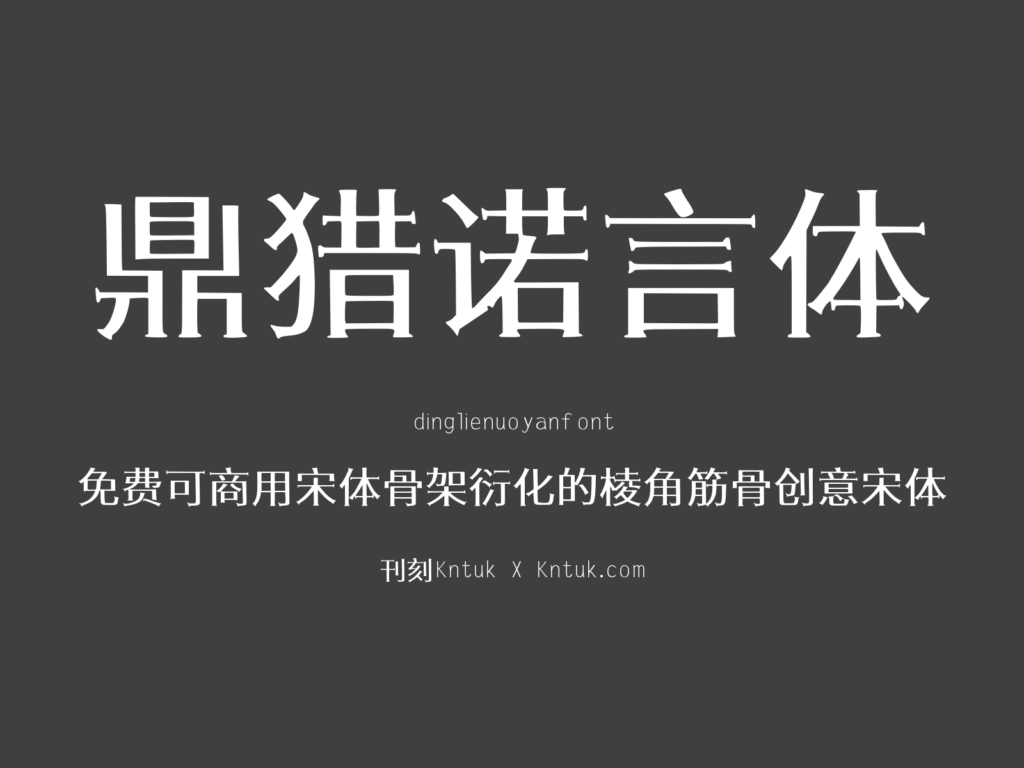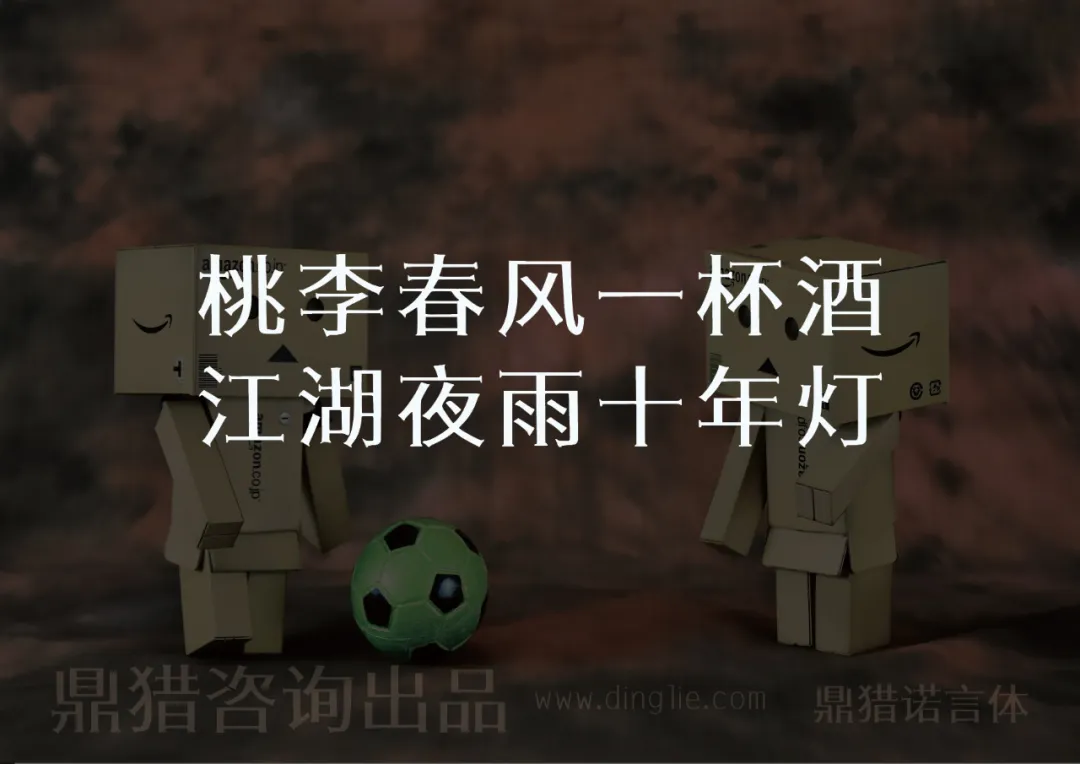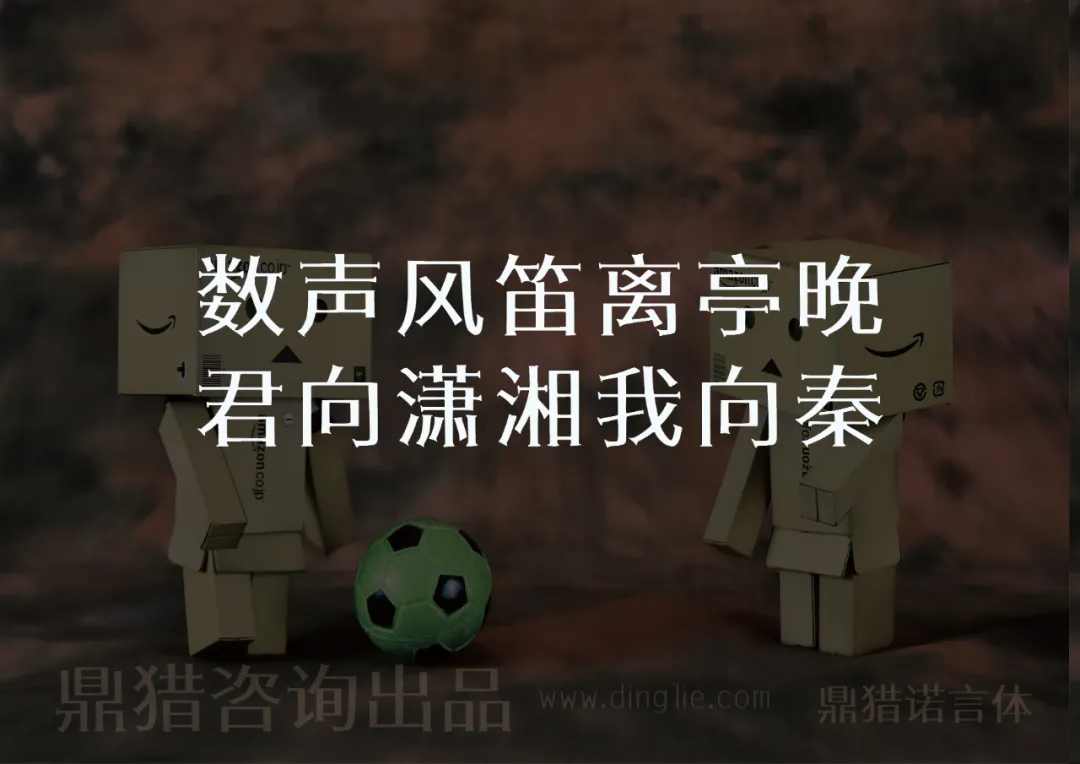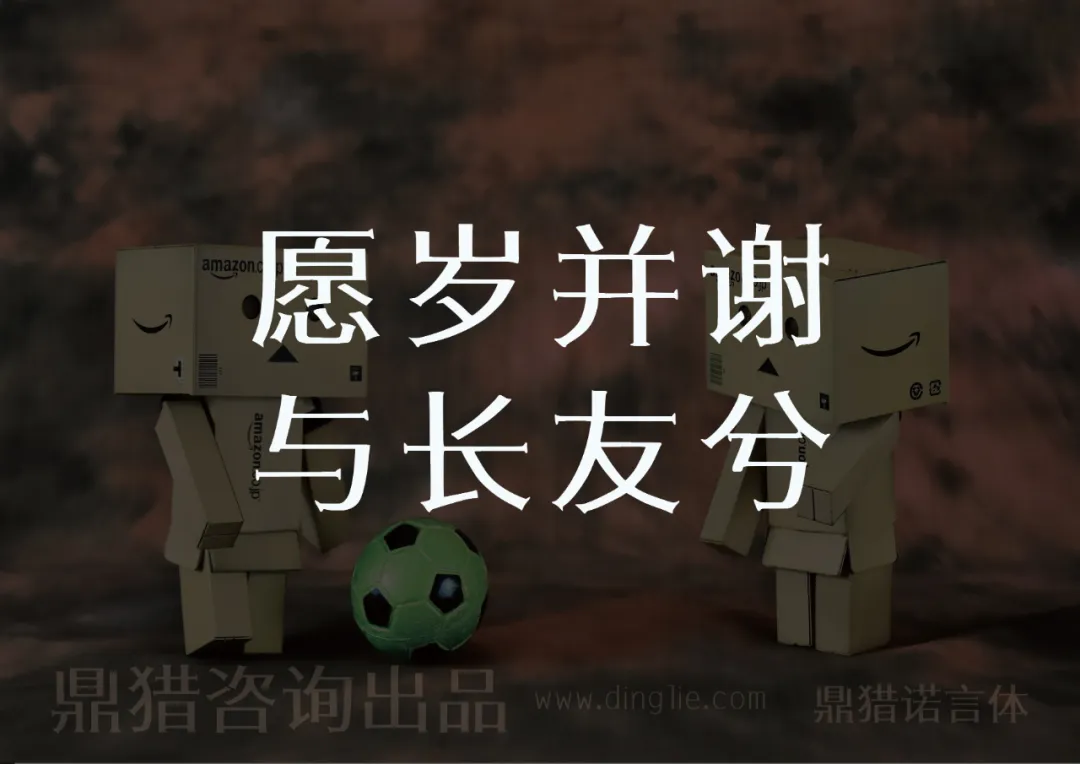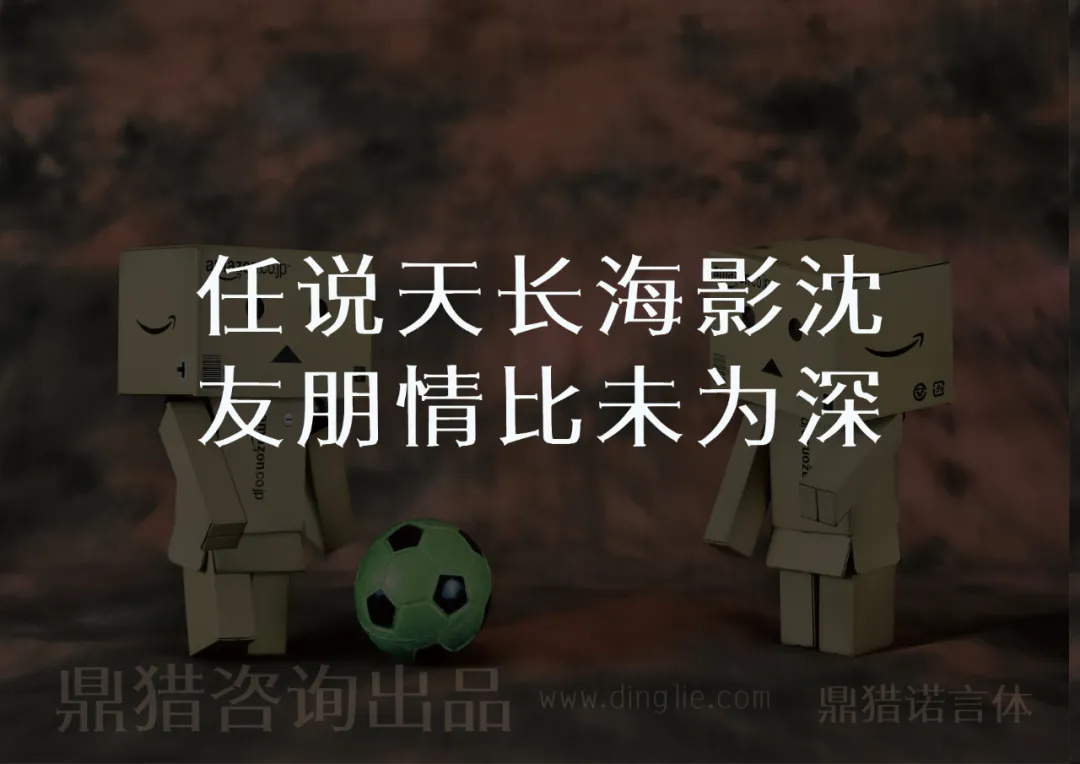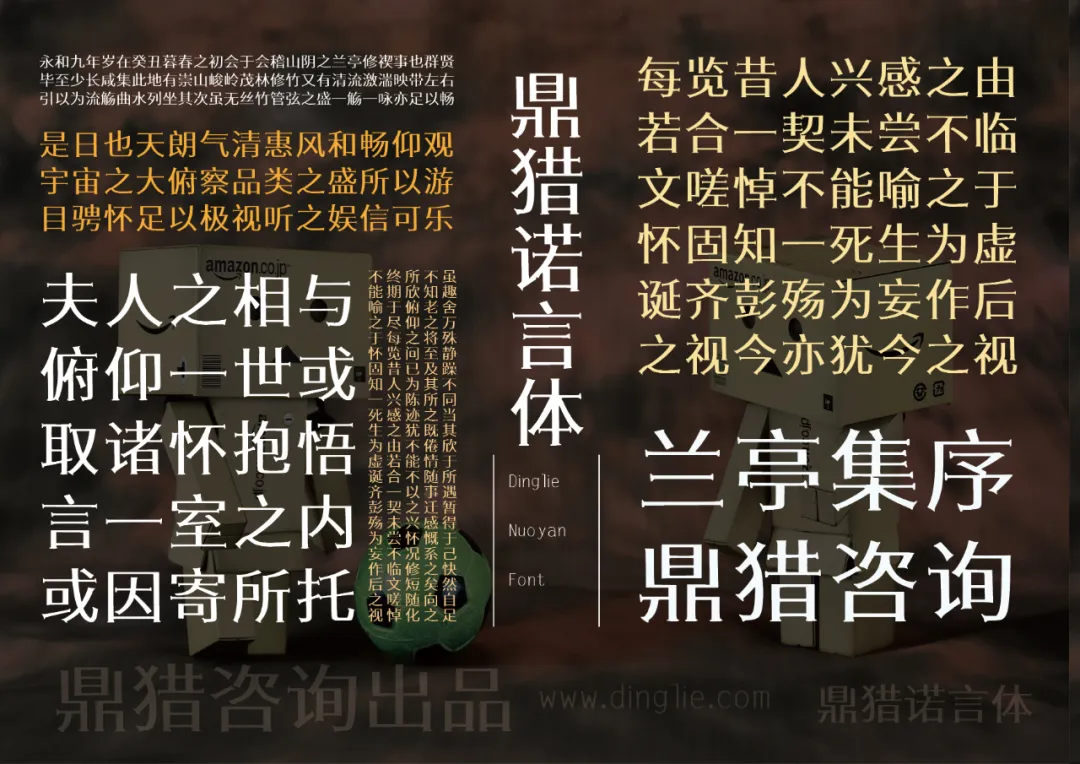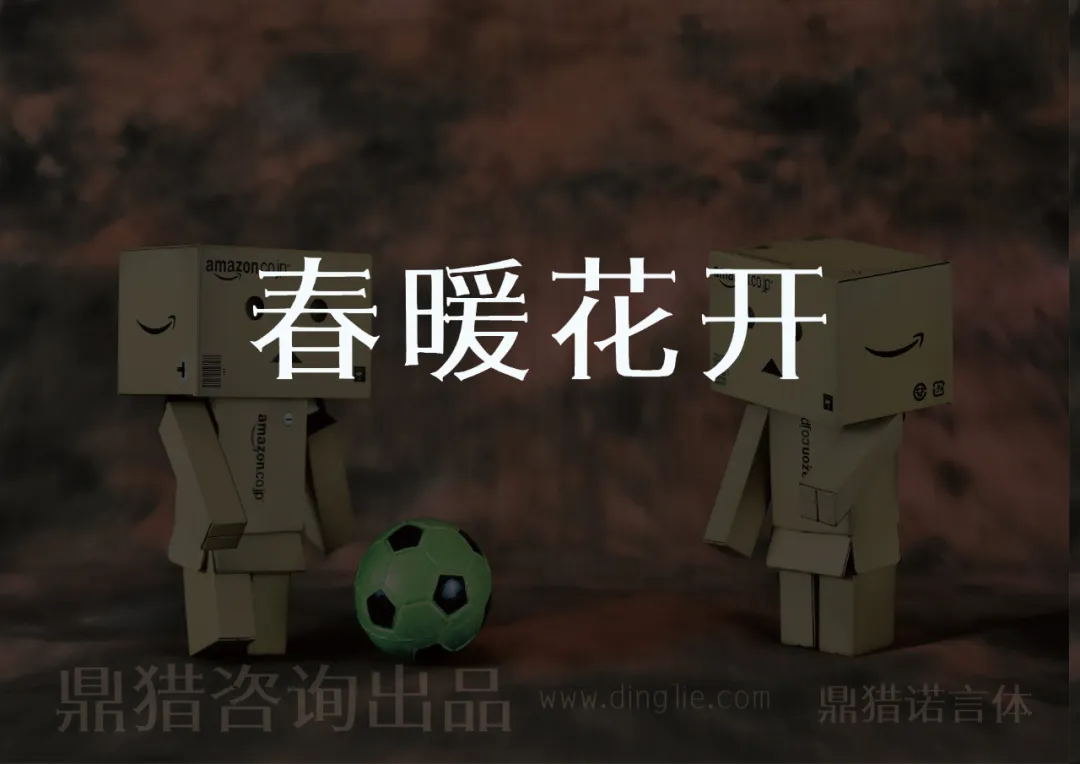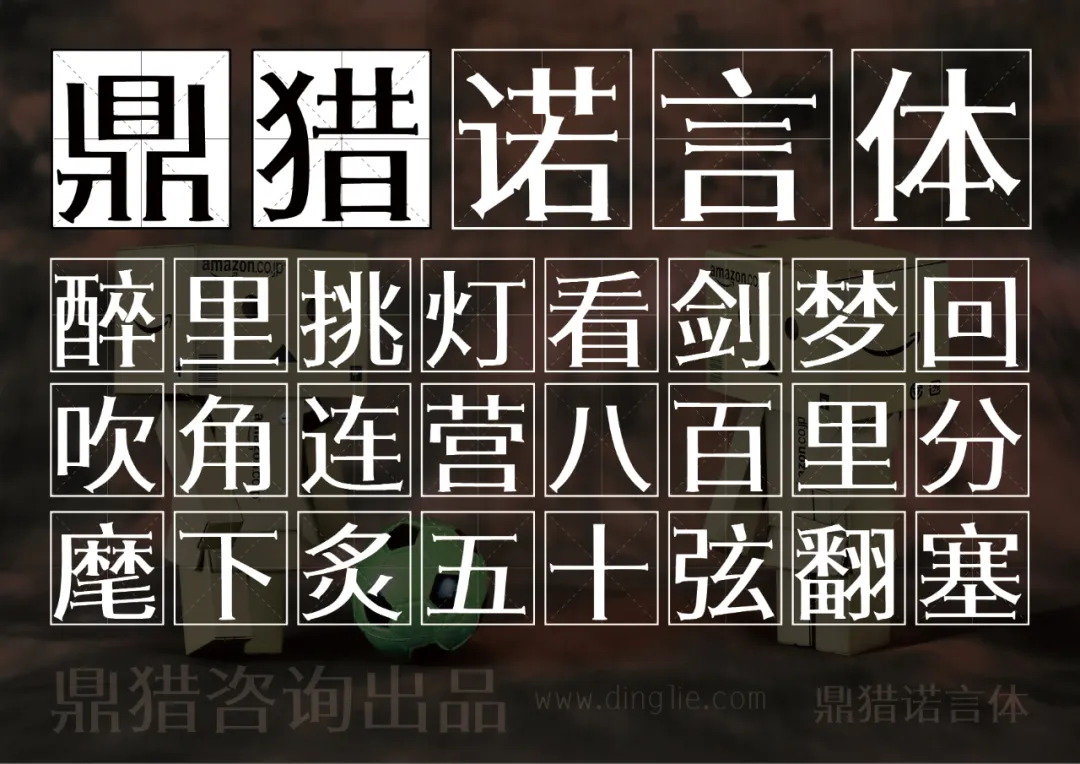
鼎猎诺言体,是一款以宋体为蓝本衍化的创意字体,整体有棱角但内里有筋骨,有着一诺千金和一言九鼎的稳健,也有自主自立的棱角。鼎猎诺言体适合美食餐饮、文化艺术展览、企业文化,以及封面杂志海报、餐饮茶饮、美妆护肤等各个行业。
鼎猎诺言体字体样张,展示“醉里挑灯看剑梦回,吹角连营八百里分,麾下炙五十弦翻塞”,底部标注鼎猎咨询出品及网址www.dinglie.com-刊刻Kntuk
鼎猎诺言体以简体中文汉字编码国家标准(GB2312编码)为标准,
共计设计了多达7415个字符,其中汉字6769个。
可以满足绝大部分印刷设计等要求。
鼎猎诺言体字体展示,以《兰亭集序》文本为例,鼎猎咨询出品,网址www.dinglie.com。-刊刻Kntuk
愿岁并谢与长友兮,两个亚马逊纸箱人中间有一个足球,鼎猎咨询出品鼎猎诺言体www.dingle.com-刊刻Kntuk
春暖花开,两个亚马逊纸箱人站在足球旁,鼎猎咨询出品,www.dinglie.com,鼎猎诺言体-刊刻Kntuk
思君若汶水,两个纸箱人中间有一个绿色足球,底部标注鼎猎咨询出品 www.dingle.com 鼎猎诺言体-刊刻Kntuk
数声风笛离亭晚,君向潇湘我向秦。鼎猎咨询出品,www.dinglie.com,鼎猎诺言体。背景是两个纸箱人和一个足球。-刊刻Kntuk
两个纸箱人旁有足球,配文桃李春风一杯酒江湖夜雨十年灯,鼎猎咨询出品 www.dinglie.com 鼎猎诺言体-刊刻Kntuk
两个纸箱人中间放着足球,配文“任说天长海影沈 友朋情比未为深”,底部有“鼎猎咨询出品 www.dinglie.com 鼎猎诺言体”-刊刻Kntuk
两个纸箱人相对而立,中间有足球,大字写着“故人相见似河清”,底部有“鼎猎咨询出品”及网址。-刊刻Kntuk